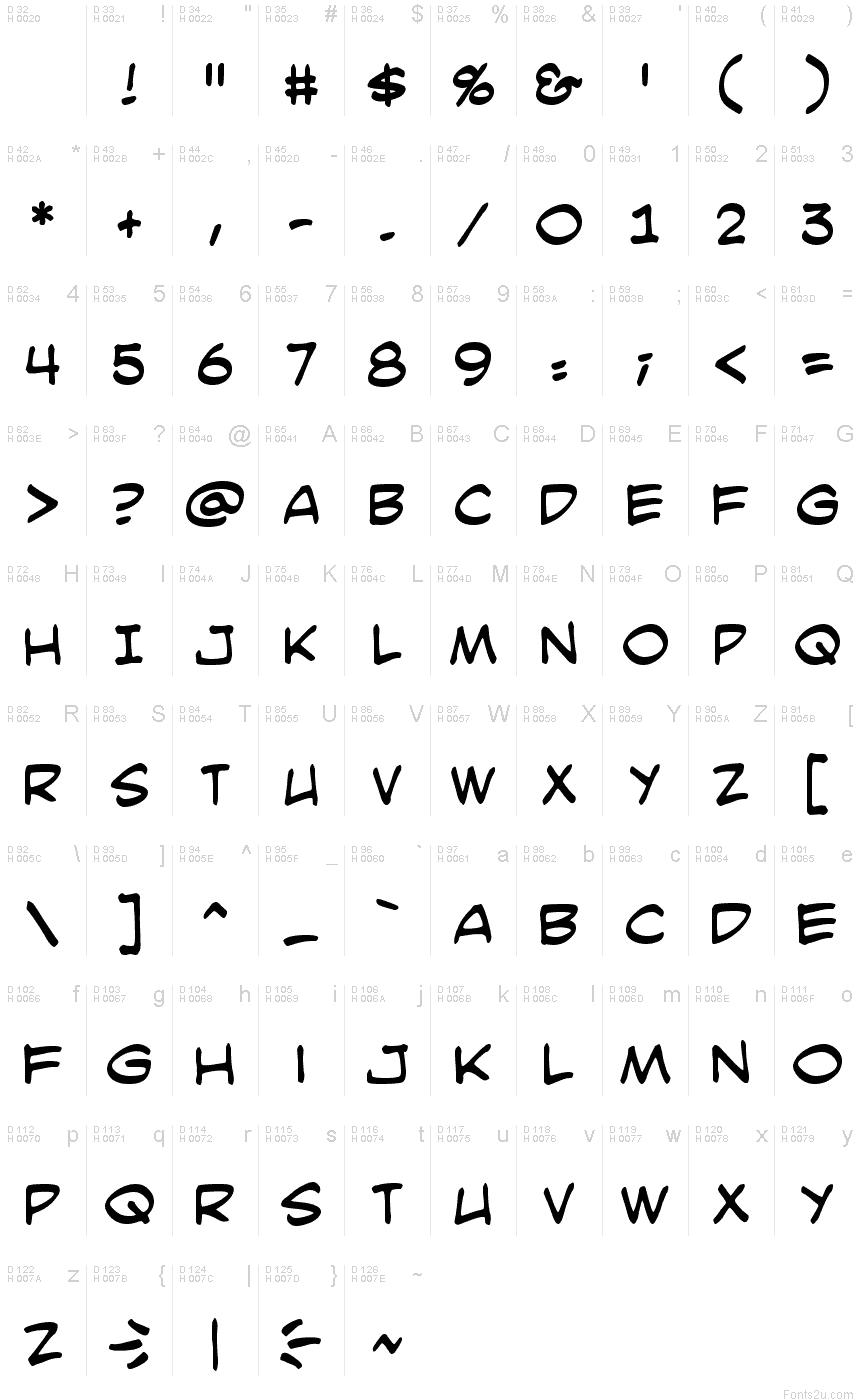
SmackAttack BB フォント
SmackAttack BB
Nate Piekos
Nate Piekosによる「Smack Attack」は、手書き風コミックフォント(大文字のみ)の無料フォントです。素早いブラシストロークによる、自由で少しやんちゃなリズムが特徴です。一気に描き上げたような書体で、幅のある曲線や詰まった結合部、不揃いな角度が、整いすぎない生き生きとしたコミックのエネルギーを表現しています。
ポスターの見出し、コミックの擬音、子供向け本の表紙、ゲームのタイトルロゴ、そして動きのあるデザインが求められるパンチの効いたグッズ制作に最適です。短いテキストやカバーコピー、あるいは大きな一言など、荒削りで弾むような大文字は、どんな単純な言葉でもページから飛び出してくるような迫力を生み出します。